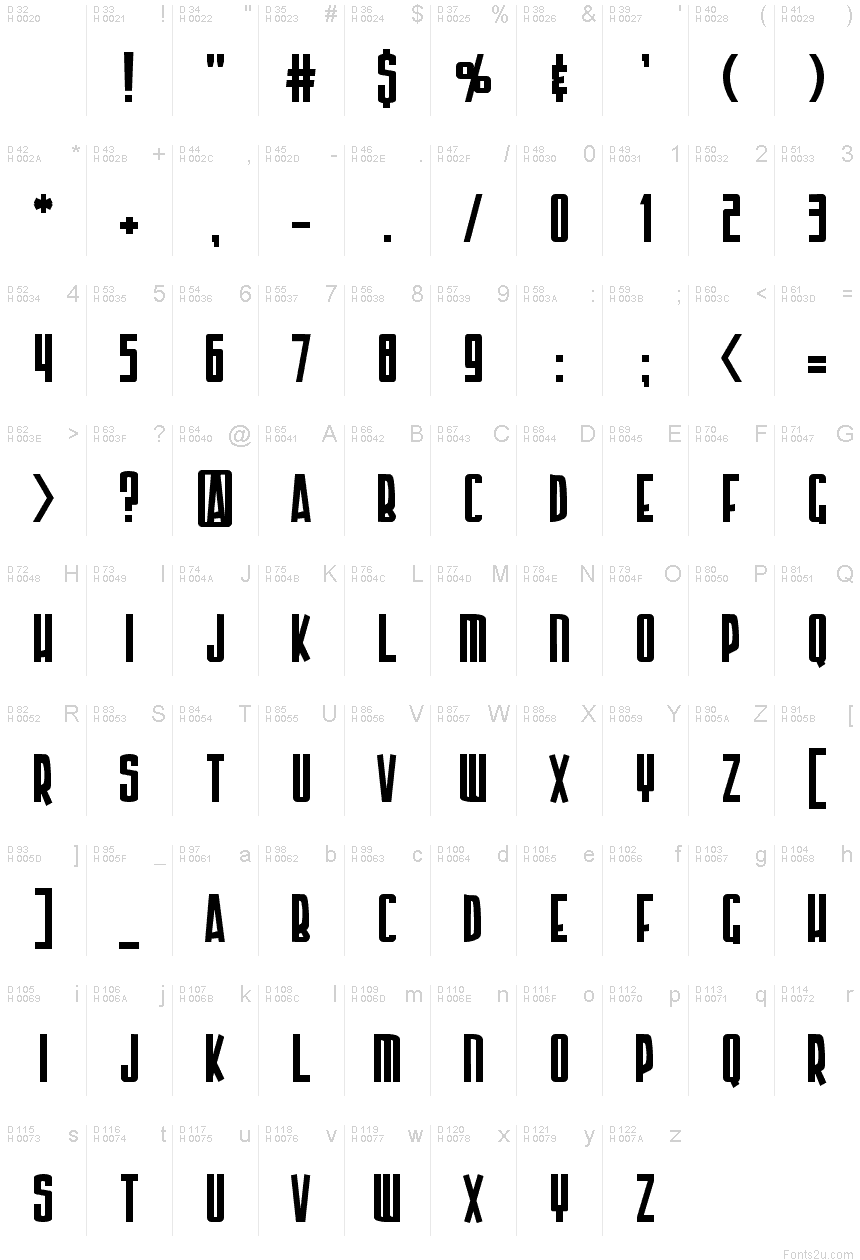
Armor Piercing od Nate'a Piekosa to darmowy, retro krój displayowy, który uderza niczym grad stalowych kolców. Jego ultra-wysokie, wąskie litery wyglądają jak wykute w metalu: sztywne pionowe kreski, ciasny odstęp i gwałtowne kąty nadają każdemu słowu skompresowany, wyrazisty charakter. Ma w sobie energię komiksów pulp, niczym tytuły starych seriali upchnięte na ziarnistym plakacie filmowym – czysta dynamika i napięcie.
Dzięki Armor Piercing nagłówki natychmiast wyglądają głośniej i groźniej, nawet zanim dodasz kolor czy teksturę. Ten darmowy font błyszczy na okładkach komiksów, logotypach gier, plakatach sci-fi, grafikach do filmów klasy B, ulotkach koncertowych i odważnym brandingu produktów z charakterem. Połącz go z prostym, szerokim krojem bezszeryfowym w mniejszych rozmiarach, aby zrównoważyć jego wąskie, strzeliste kształty i zachować czytelność.
Armor Piercing